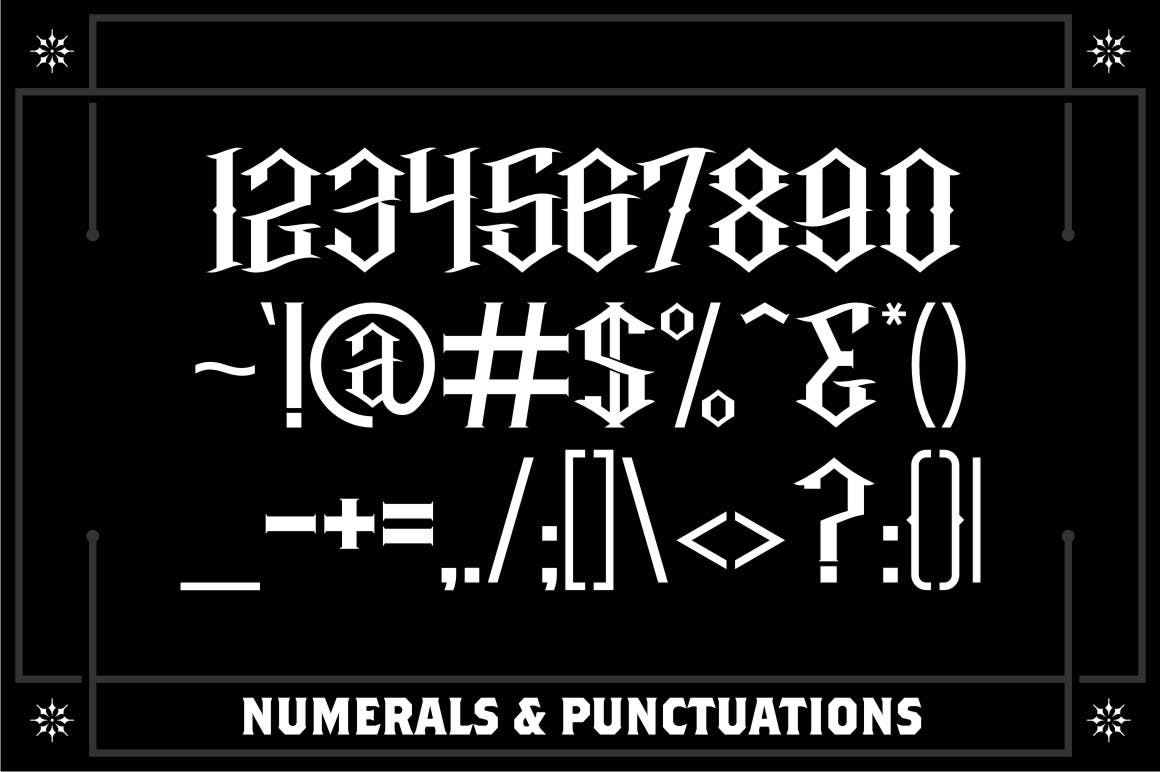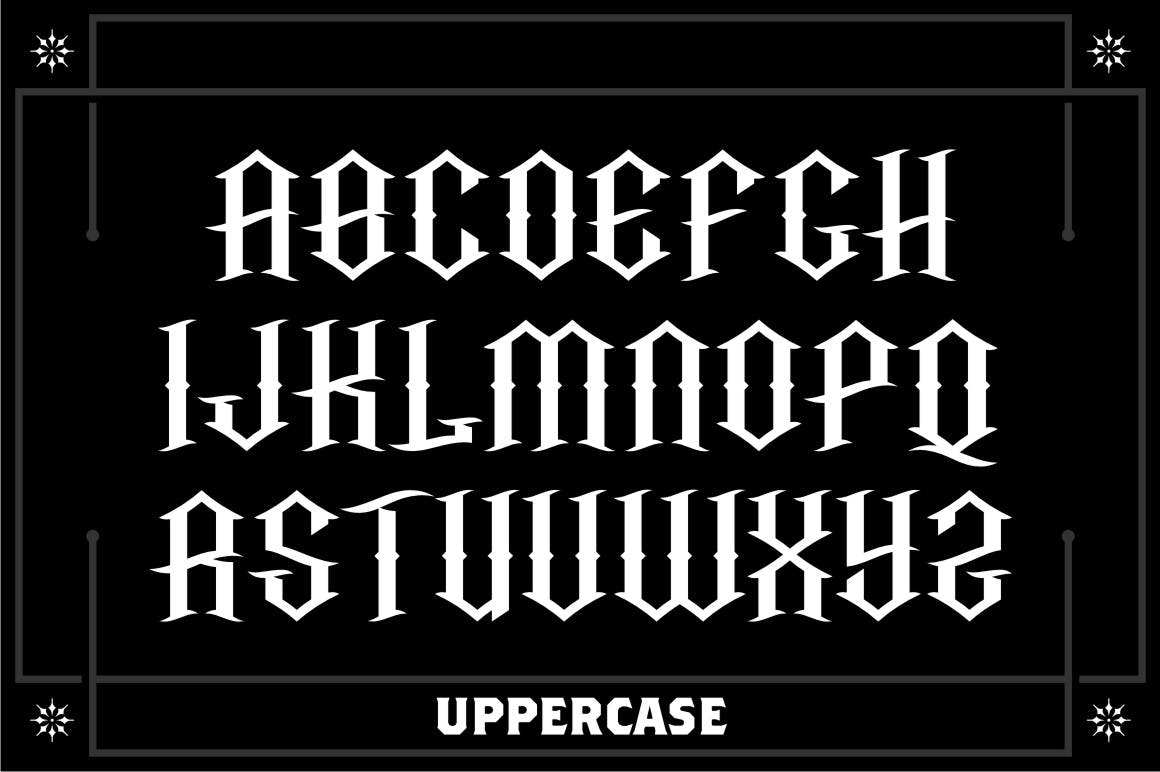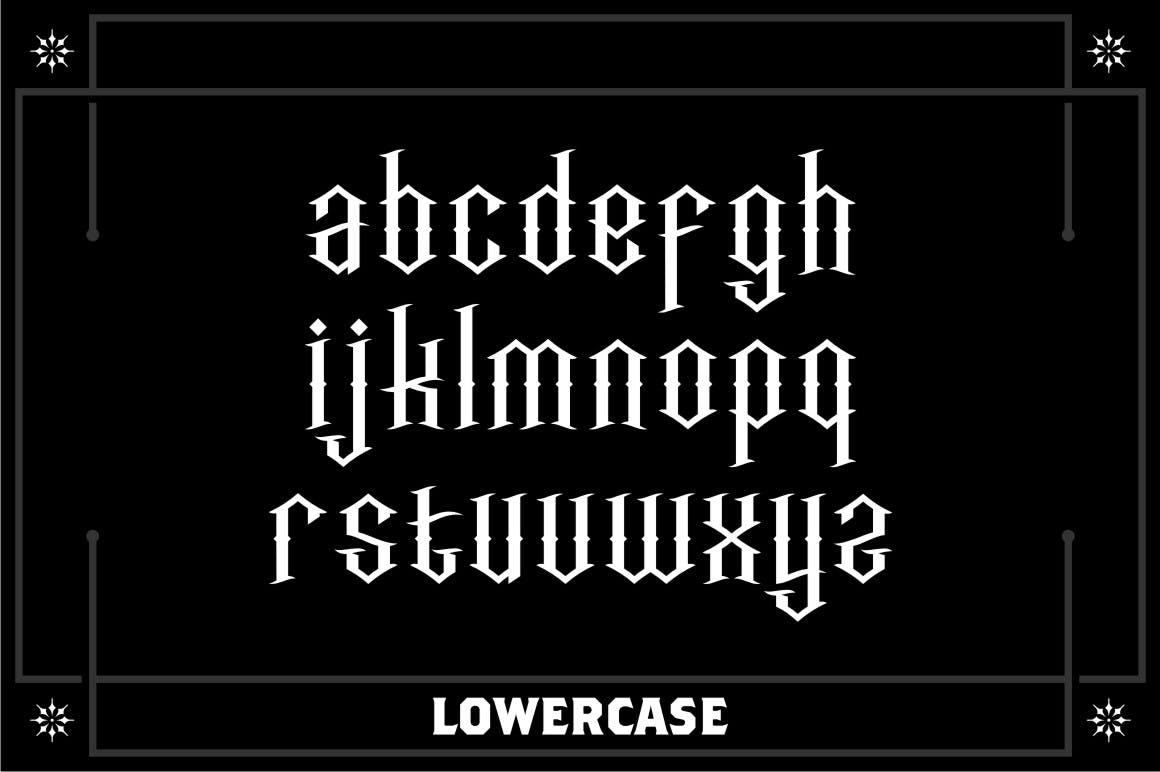
فونت Incognito یک فونت کلاسیک بلک لتر است که به شدت تحت تأثیر فرهنگ تتو و کستوم کالتور قرار دارد. این فونت بهترین گزینه برای طراحیهای گوتیک، قبیلهای و موضوعات تتو میباشد. این فونت در دو فرمت رایج (OTF و TTF) در دسترس است.